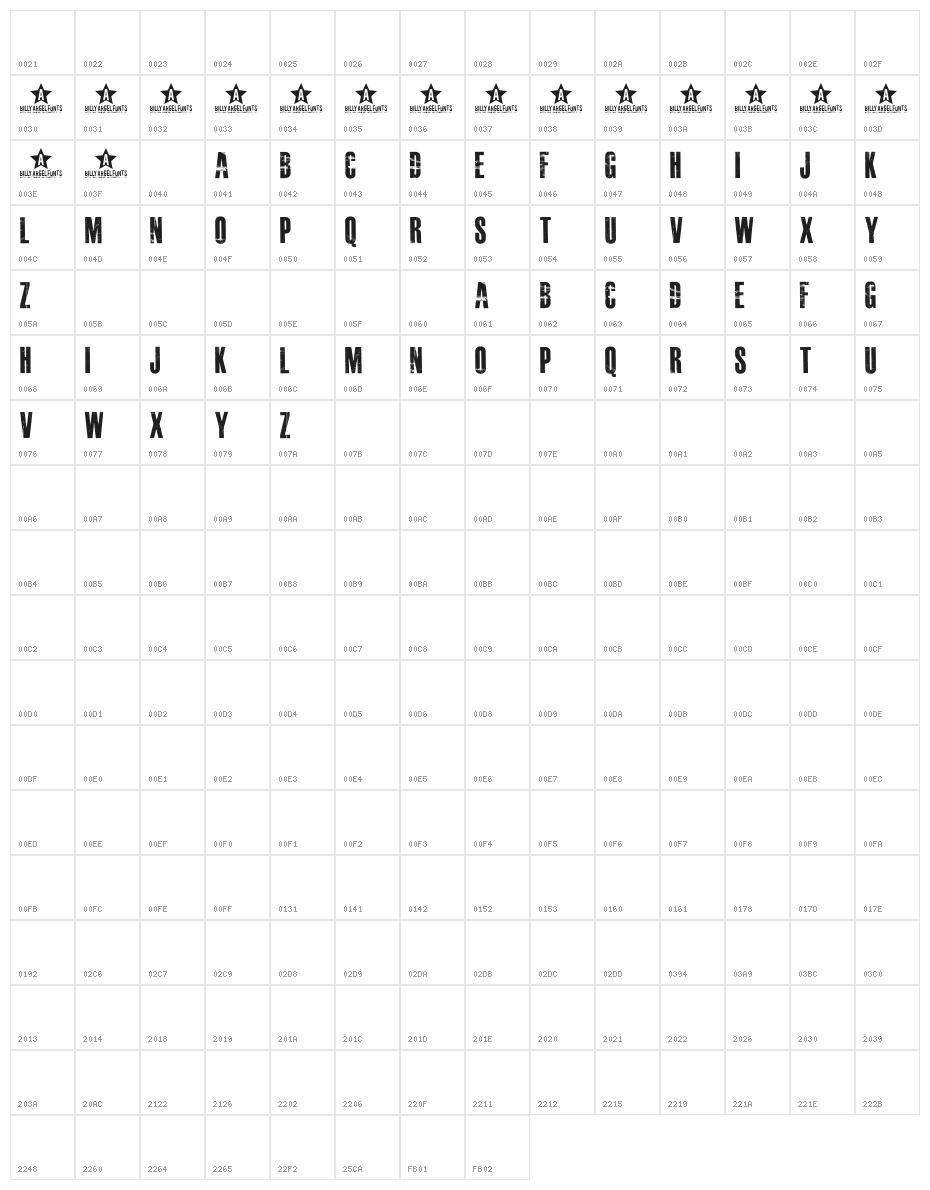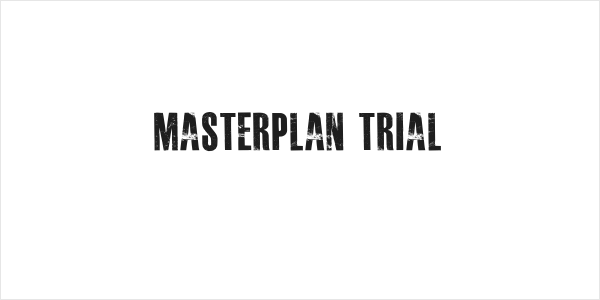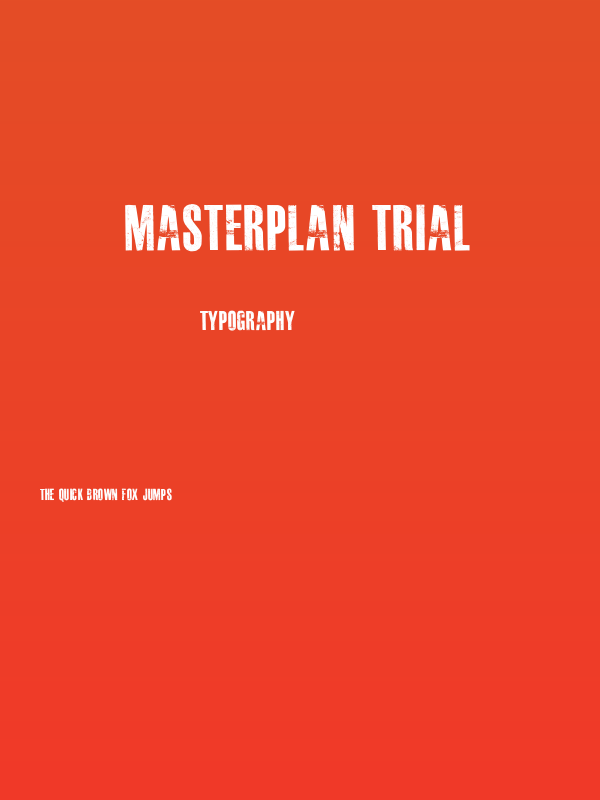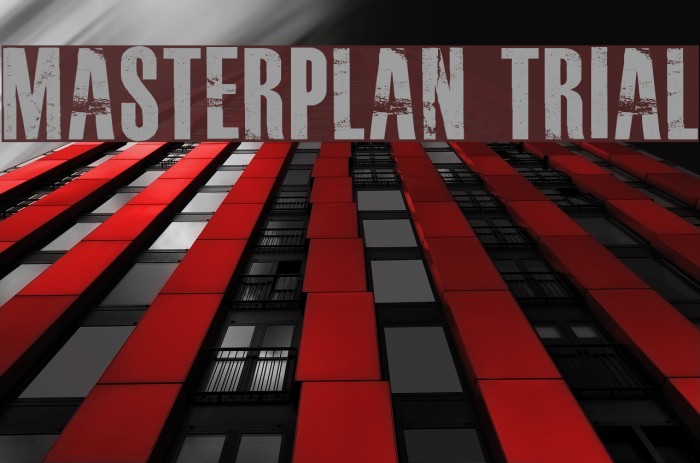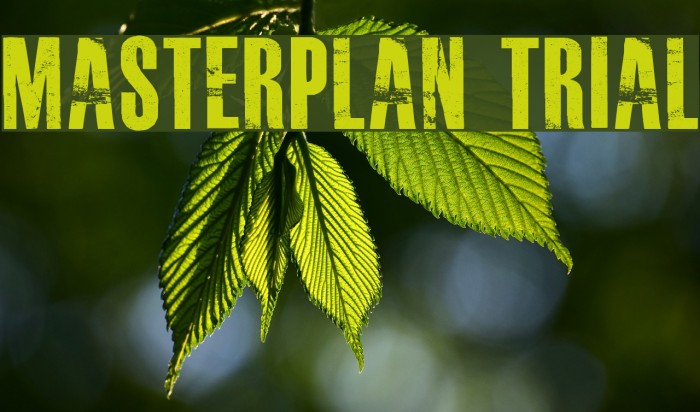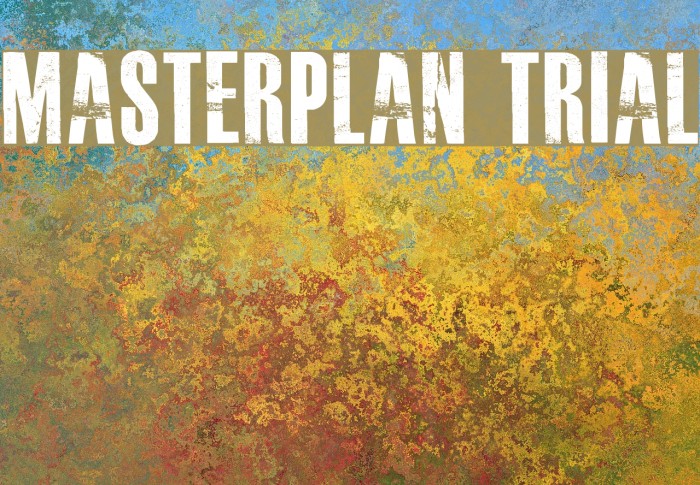
MASTERPLAN TRIAL Font
✎ Messy
| Proiecte propuse | Ideal for posters, album covers, branding projects, and any design requiring a strong, vintage aesthetic. |